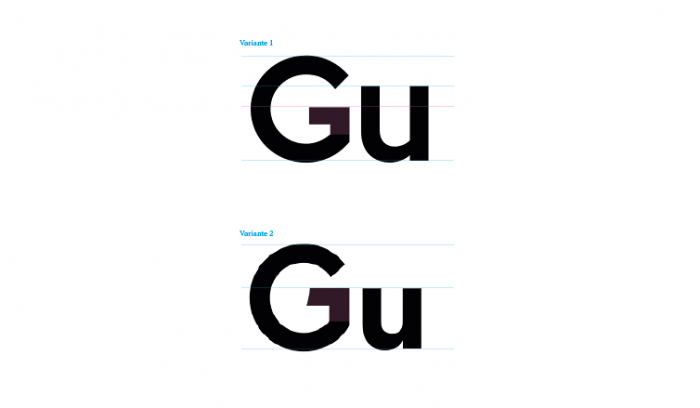
Branding. Schriftart gesucht. Harmonie zwischen "G" und "u"
ich bin gerade dabei das gesamte CD eines Unternehmens zu gestalten. Das vorhandene Logo bekommt ein Redesign, welches auch ziemlich fertig ist. Ich bin nun an eine Stelle angelangt, wo ich sehr gerne Tipps und Meinungen von reinen TypografInnen hören würde.
Den gesamten Namen des Unternehmens kann ich leider (noch) nicht erwähnen.
Habe versucht in meiner Bibliothek eine Antwort zu finden (The Elements of Typographic Style - R. Bringhurst), aber da war nichts, oder nichts gesehen.
Die ersten zwei Buchstaben des Logos sind "G" und "u" - hier gibt es bei verschiedenen Schriftarten (serifenlos) verschiedene Positionierungen was die Mittellänge und Oberlänge anbelangt. Unten sind zwei Bilder, um besser erklären zu können, was ich meine.
Ich weiß leider nicht, wie man das Teil vom "G", welches nach links reingeht nennt. Würde gerne eure Meinung dazu hören, ob Variante 1 oder 2 typografisch besser, schöner oder passender ist.
Kennt ihr vielleicht eine passende Schriftart (sollte serifenlos sein)? Was eventuell wichtig ist, das Unternehmen beschäftigt sich mit Kindern und Neugeborenen. Soll modern sein, aber nicht zu kantig. Oder wisst ihr, wo ich sonst gute Fonts finden kann         außer bei myfonts.com?
Tja ... wenn nach Gu nur noch ein t kommt ist es etwas anderes, als wenn nach Gu vielleicht noch tenbergische Gesellschaft für die frühkindliche Erziehung oder ähnliches folgt. Somit also leider nicht zu beurteilen und nahezu unmöglich eine Meinung ab zu geben.
Würde es viel ausmachen, was nach "Gu" kommt? Bzw. was ist "anders" wenn zB ein "t" danach kommt? Was wäre der Unterschied zwischen "Gut" und "Gutenberg" - was die Typografie der Ober- und Mittellänge angeht?
das macht sehr viel aus zu wissen was für weitere zeichen kommen, ohne das wort zu kennen ist es schlecht zu beurteilen welche schrift besser wirkt.
welche wirkung du auch erreichen möchtest bzw. wie das ganze erscheinungsbild wirken soll spielt auch eine wichtige rolle. nur ein »Gu« (serifenlos) und das info, dass sie sich mit kindern beschäftigen ist ein rätsel und keine frage. sie können bekleidung, essen, medizin herstellen …
man kann dir gar nicht helfen, nicht ernsthaft.
Seh ich jetzt einen Tick anders als meine beiden Vorschreiber. Da allein nach der typografischen Präferenz gefragt ist, der Stil ja ohnehin schon ein stückweit vorgegeben ist, trau ich mir jetzt schon zu sagen, daß mir die erste Variiante allein schon ob der größeren Eindeutigkeit eher zusagt. Die Radien beim „u“ könnt ich mir aber etwas kleiner vorstellen.
das macht sehr viel aus zu wissen was für weitere zeichen kommen, ohne das wort zu kennen ist es schlecht zu beurteilen welche schrift besser wirkt.
welche wirkung du auch erreichen möchtest bzw. wie das ganze erscheinungsbild wirken soll spielt auch eine wichtige rolle. nur ein »Gu« (serifenlos) und das info, dass sie sich mit kindern beschäftigen ist ein rätsel und keine frage. sie können bekleidung, essen, medizin herstellen …
man kann dir gar nicht helfen, nicht ernsthaft.
Danke für dein Feedback. Ich gebe dir Recht, was Infomationen anbelangt und wichtig ist den gesamten Namen zu betrachten. Jedoch ist meine Frage spezifisch was "G" und "u" anbelangt. Ich würde gerne erfahren, welche der zwei Varianten oben typografisch besser ist (unter anderem unabhängig vom Logo und Geschäft). Oder betrachten wir den Namen "Gutenberg" - würdest du als Typograf die Variante 1 anwenden oder 2?
Seh ich jetzt einen Tick anders als meine beiden Vorschreiber. Da allein nach der typografischen Präferenz gefragt ist, der Stil ja ohnehin schon ein stückweit vorgegeben ist, trau ich mir jetzt schon zu sagen, daß mir die erste Variiante allein schon ob der größeren Eindeutigkeit eher zusagt. Die Radien beim „u“ könnt ich mir aber etwas kleiner vorstellen.
Ist es eine Geschmackssache, oder gibt es hier typografische Gründe?
Aus Sicht der Schriftgestaltung haben die beiden Linien (Oberkante des G-Querstrichs und x-Höhe) nichts miteinander zu tun. Der Querstrich des G sitzt optisch mittig oder unterhalb der Mitte. Die x-Höhe ist dagegen bei den meisten Schriften deutlich höher. Somit gibt es bei den meisten Schriften auch keinen Zusammenhang.
In einem Logo kannst du natürlich machen was du möchtest. Es ist dann viel eher eine Frage, ob der künstlich hochgezogene Querstrich dann eventuell unnatürlich aussieht. Aber das sieht man dann eben am besten, wenn man das Wort als ganzes anschaut.
Danke für dein Feedback. Ich gebe dir Recht, was Infomationen anbelangt und wichtig ist den gesamten Namen zu betrachten. Jedoch ist meine Frage spezifisch was "G" und "u" anbelangt. Ich würde gerne erfahren, welche der zwei Varianten oben typografisch besser ist (unter anderem unabhängig vom Logo und Geschäft). Oder betrachten wir den Namen "Gutenberg" - würdest du als Typograf die Variante 1 anwenden oder 2?
ich kann es nicht pauschal antworten. für ein logo ist fast alles möglich. ein richtig und falsch in deinen beispielen gibt es nicht.
Ich weiß leider nicht, wie man das Teil vom "G", welches nach links reingeht nennt.
Querstrich. Er wird aber normalerweise nicht in das G ‘hineingeschrieben’, es ist einfach der Strichansatz des vertikalen Striches. Deshalb läuft er von links nach rechts.